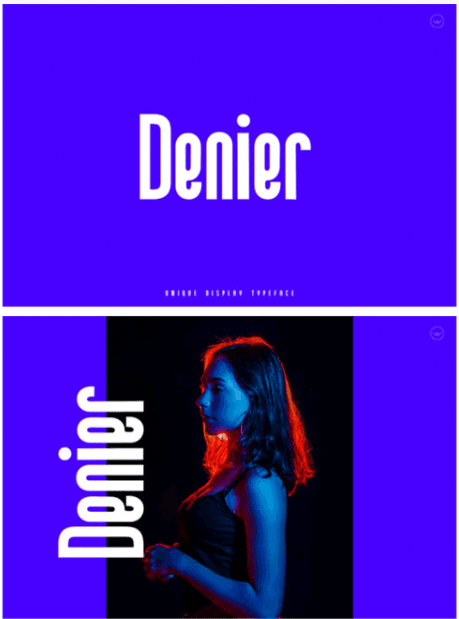
Denier Font
Denier - это современный и чистый дисплейный шрифт. Его универсальность и аккуратный вид украсят каждый ваш дизайн. Получайте удовольствие от этого красивого шрифта и исследуйте его бесконечные вариации.